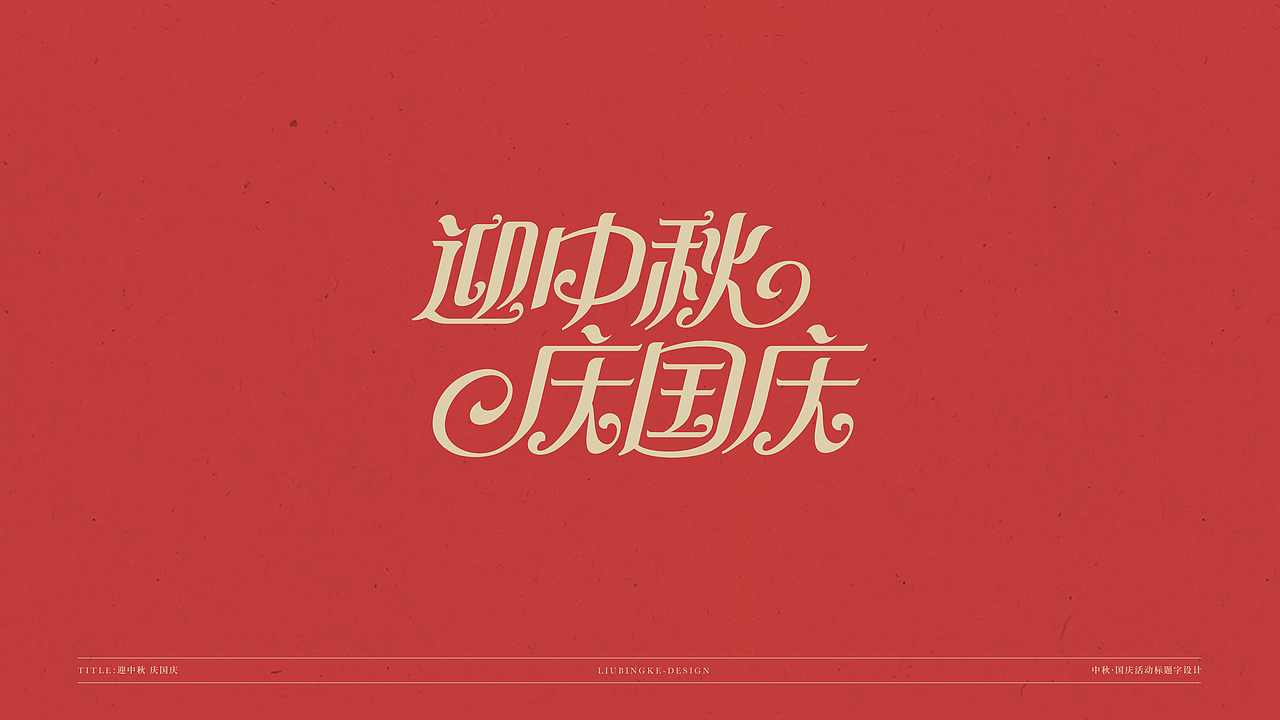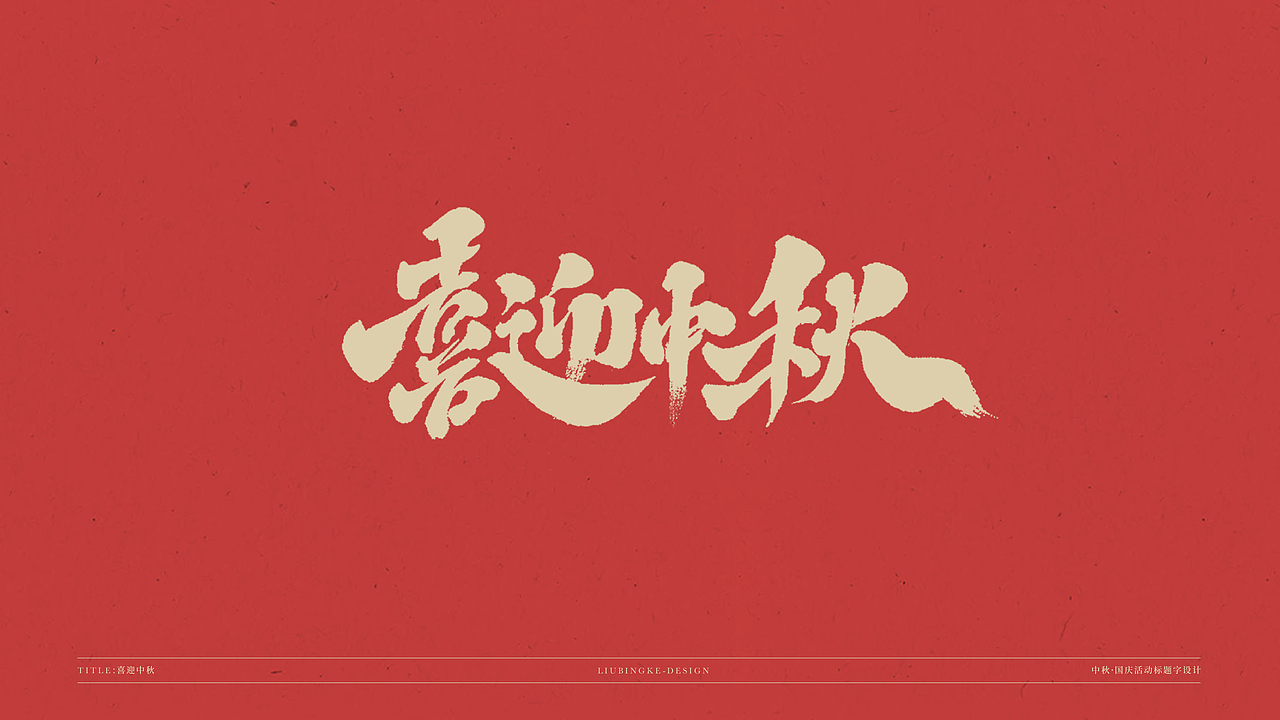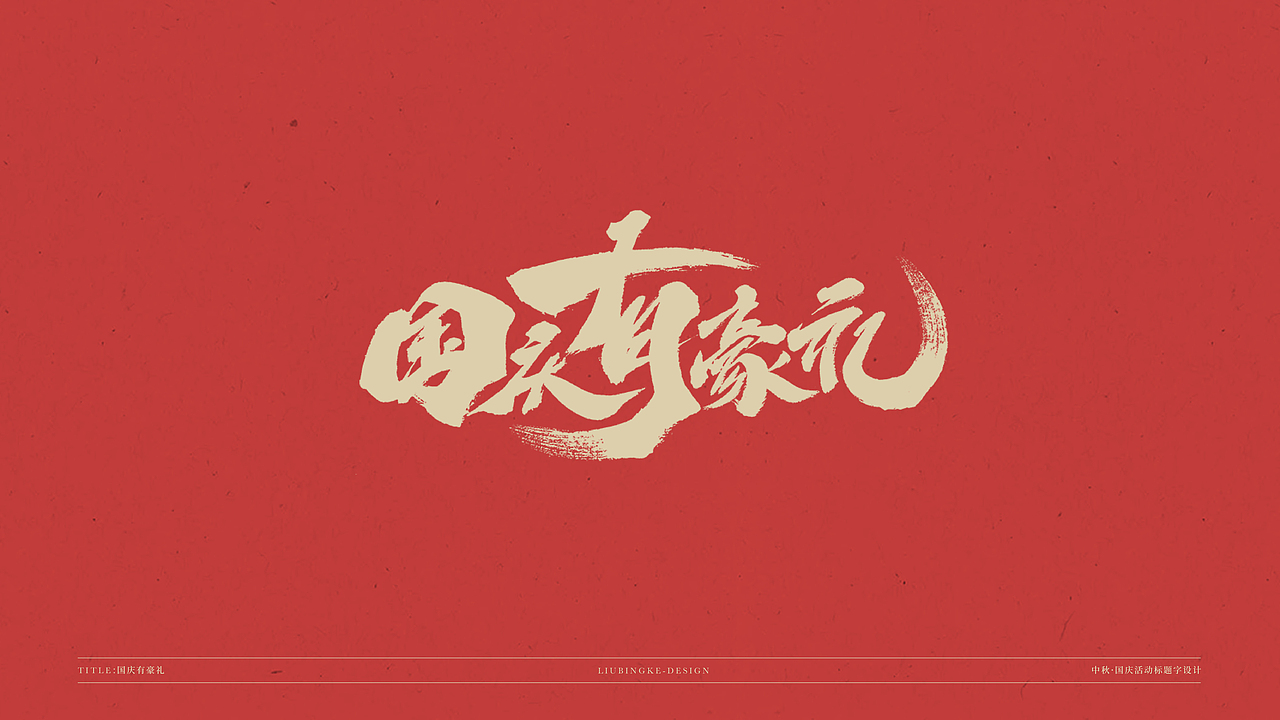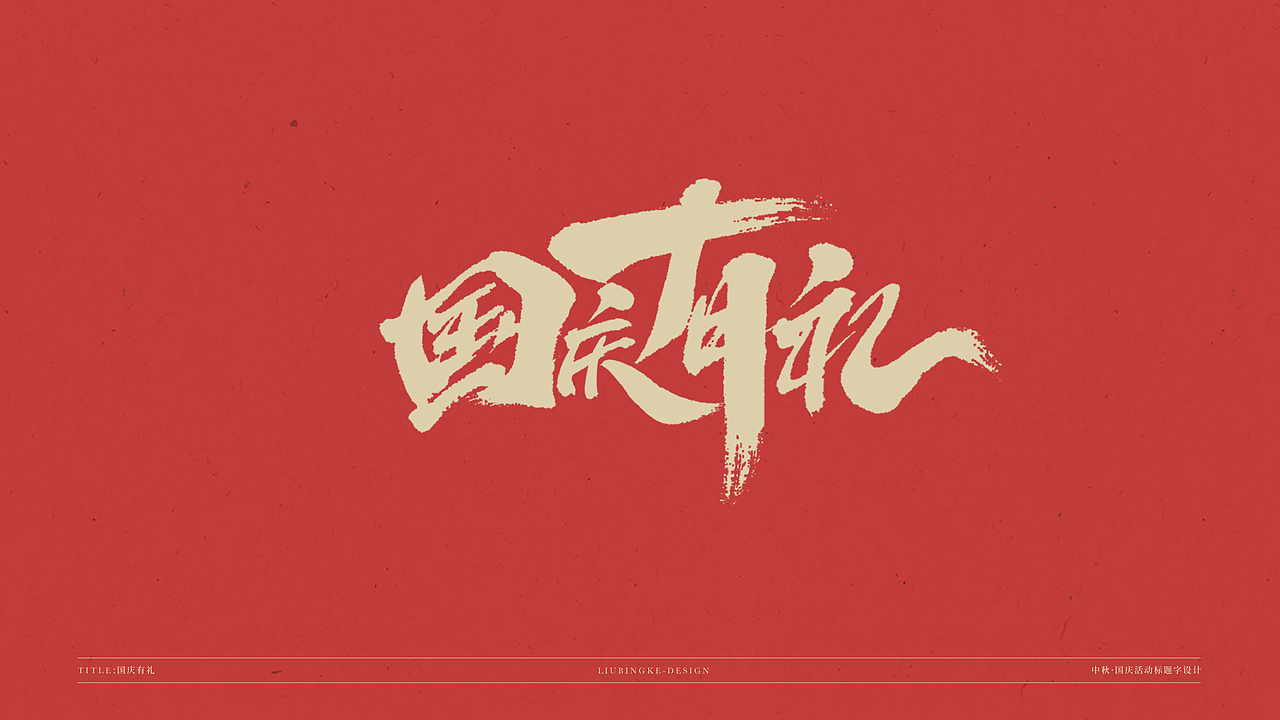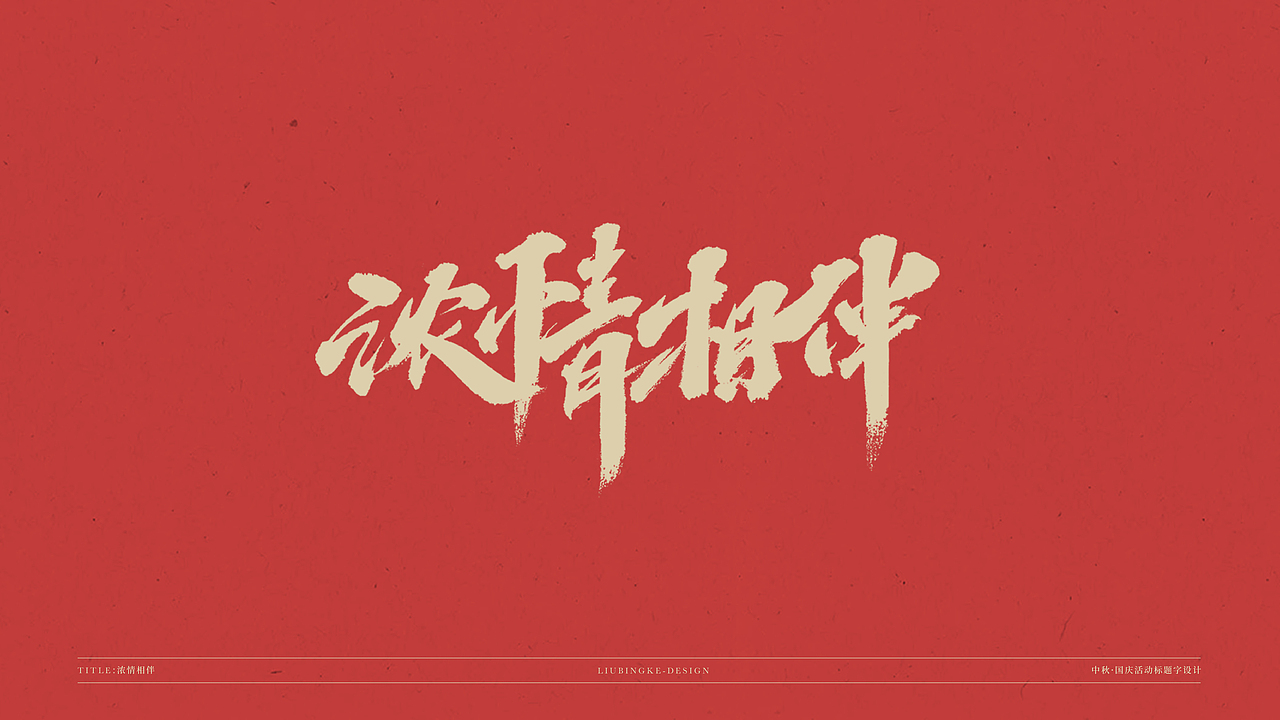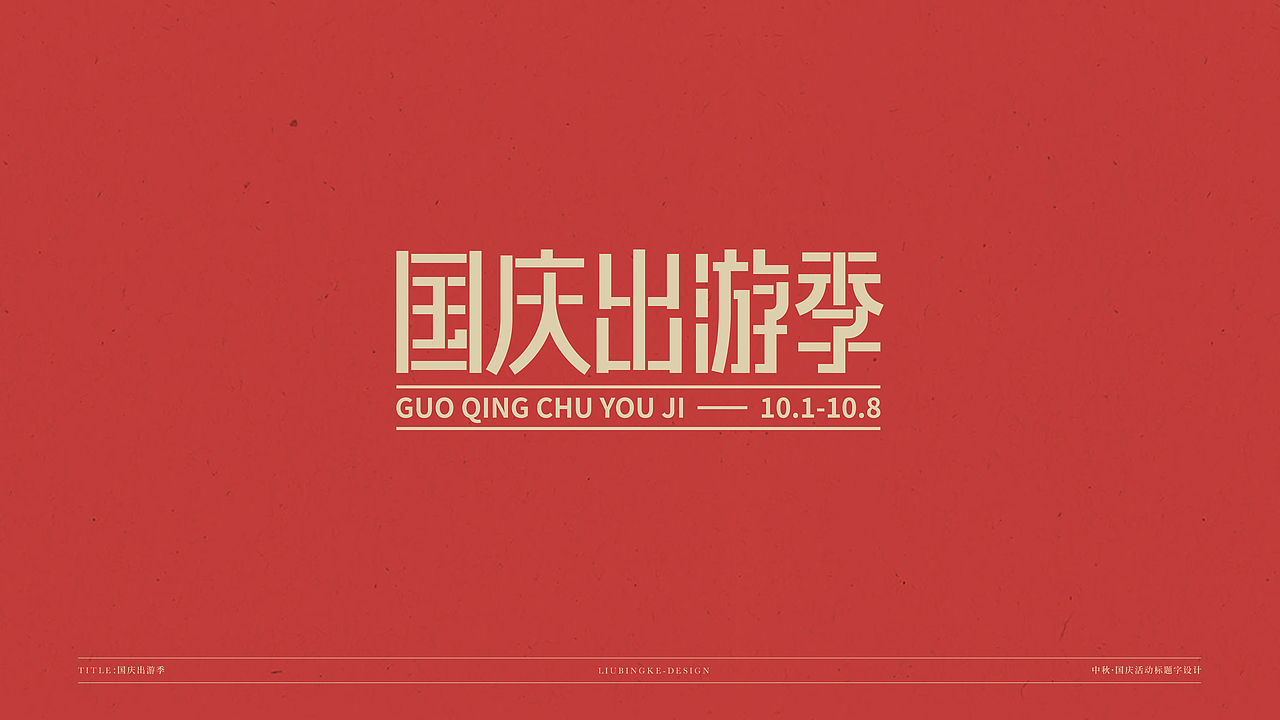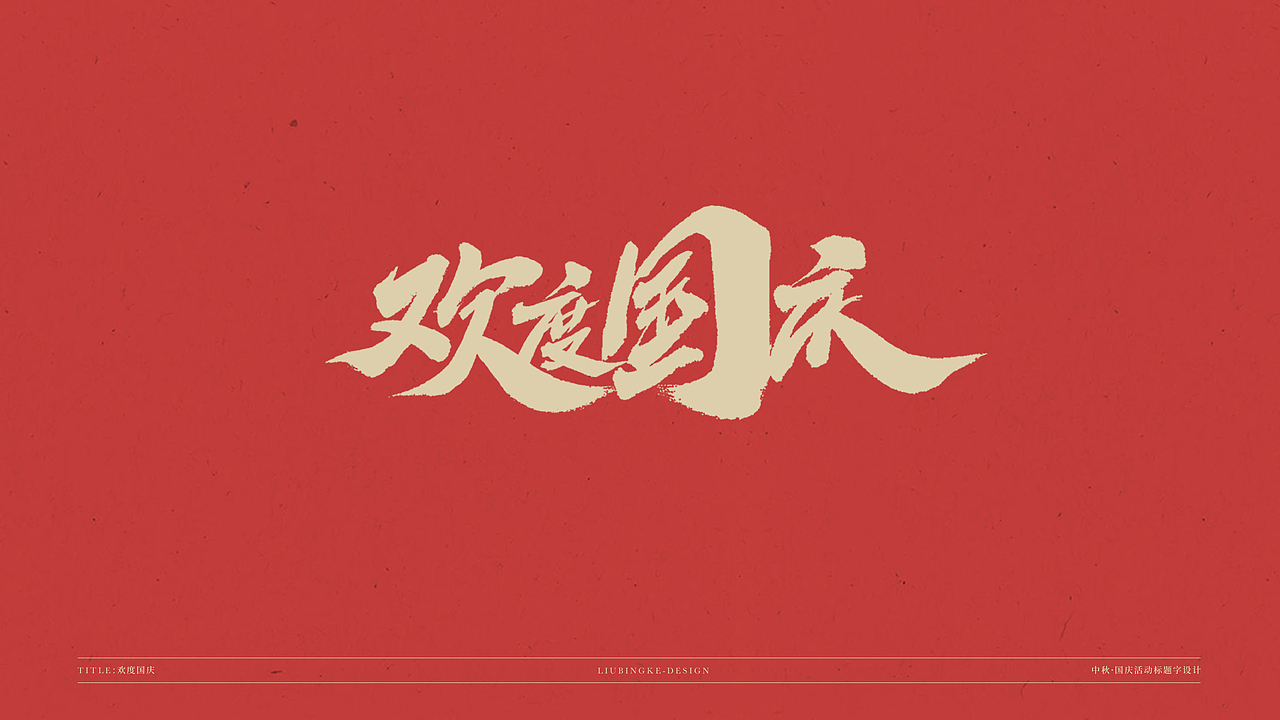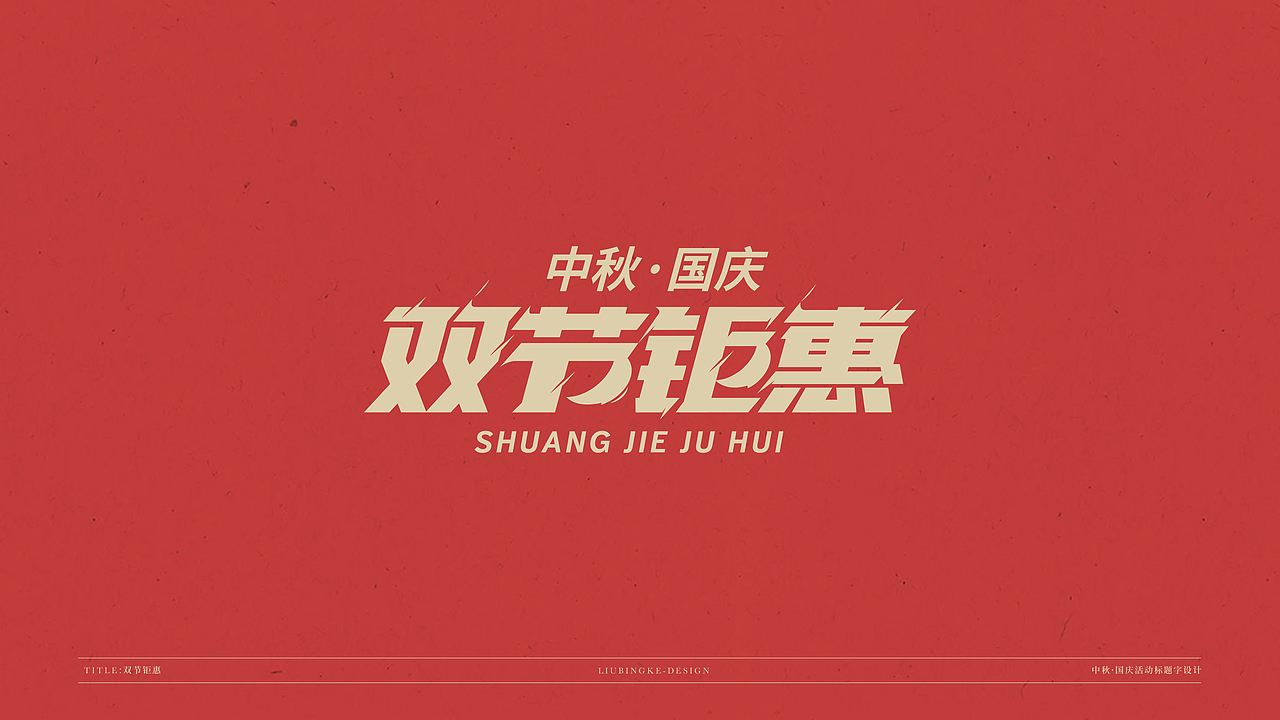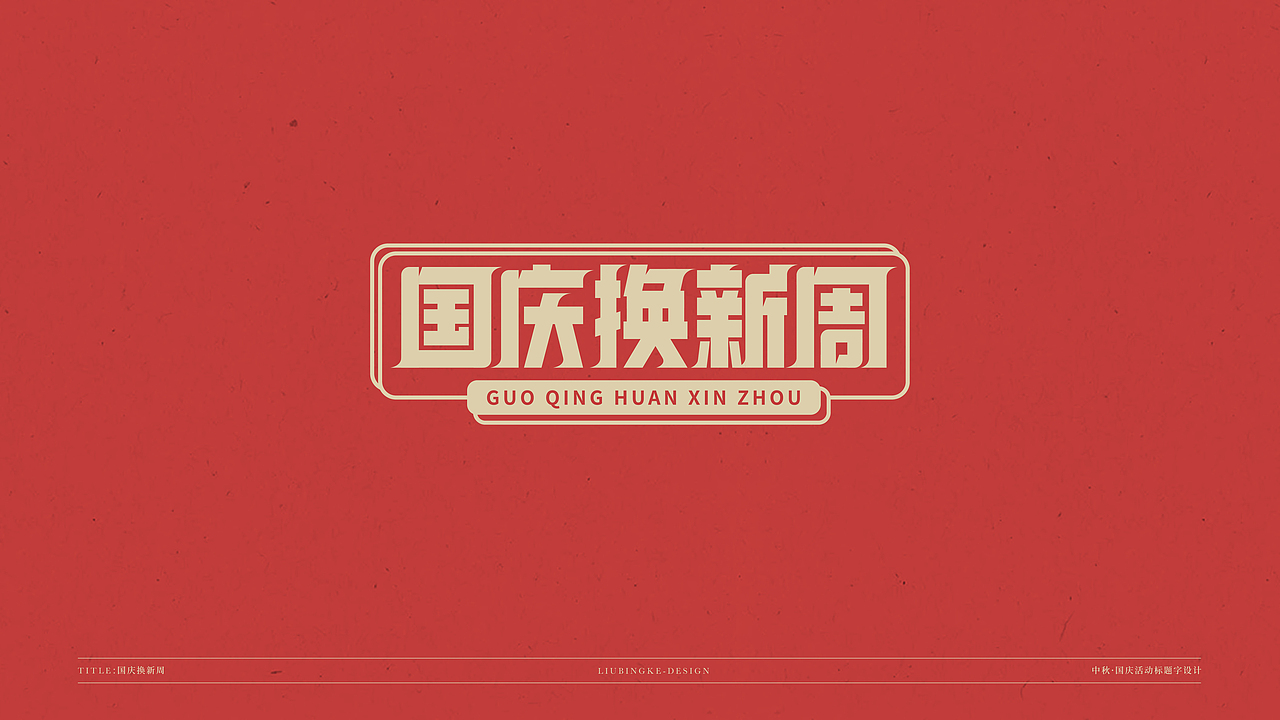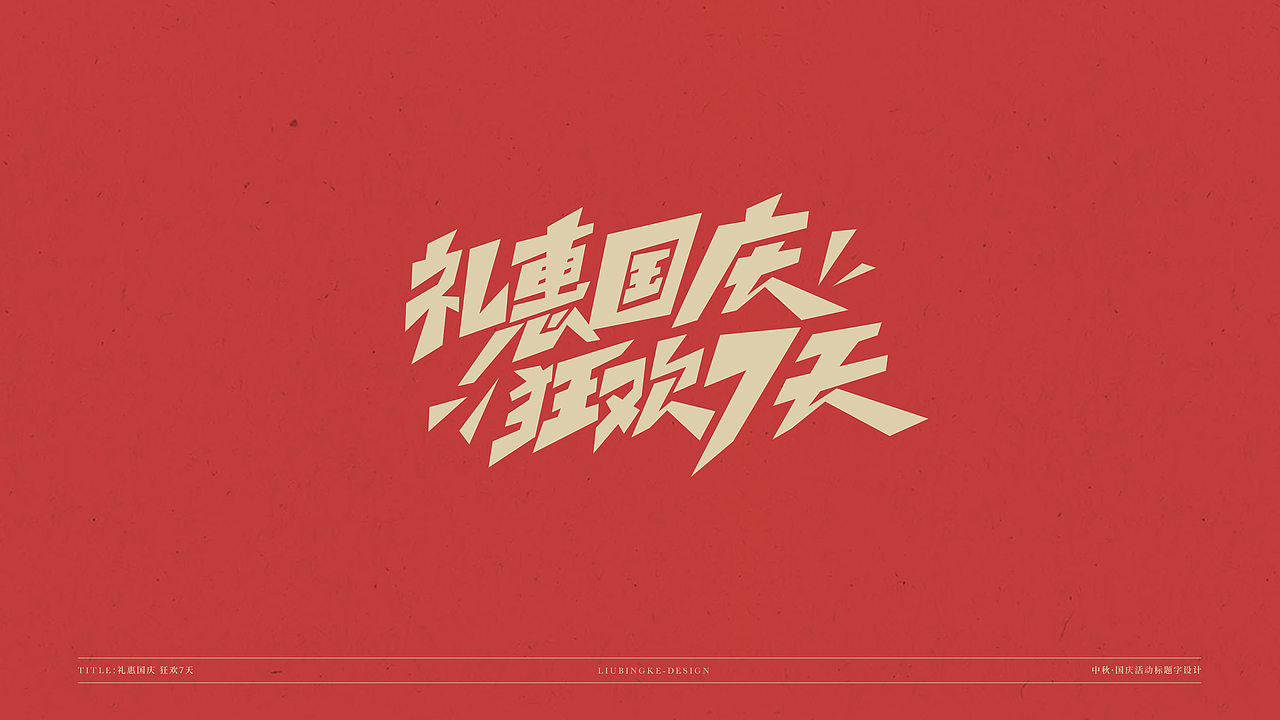
国庆&中秋-免费标题字体
今年,国庆中秋同一天,最长的假期即将到来,
作为设计师来讲,迎接假期,肯定会有很多标题字体需要设计,
所以,前一阵,组织工作室几位小伙伴,做了这一份国庆节中秋节的免费字体礼包,
有字形设计,也有书法字体,可以说是比较全面了,
如果你恰好需要,那么,这些字体可能会帮到你。
每一个字体,我们都保留了设计步骤,
一方面方便大家根据工作需要做出修改,
另一方面,每一个步骤,可以算是一个小小的设计教程了,
这是这次分享的特别之处,